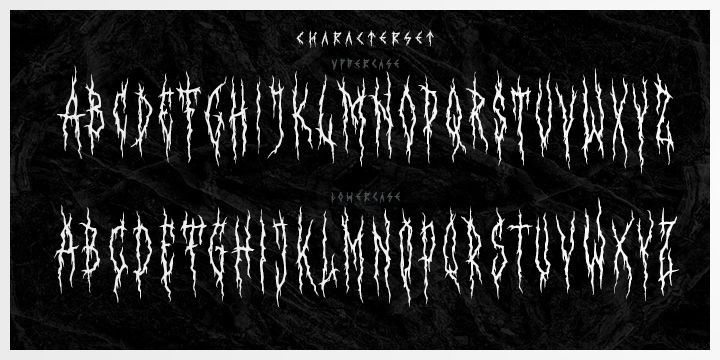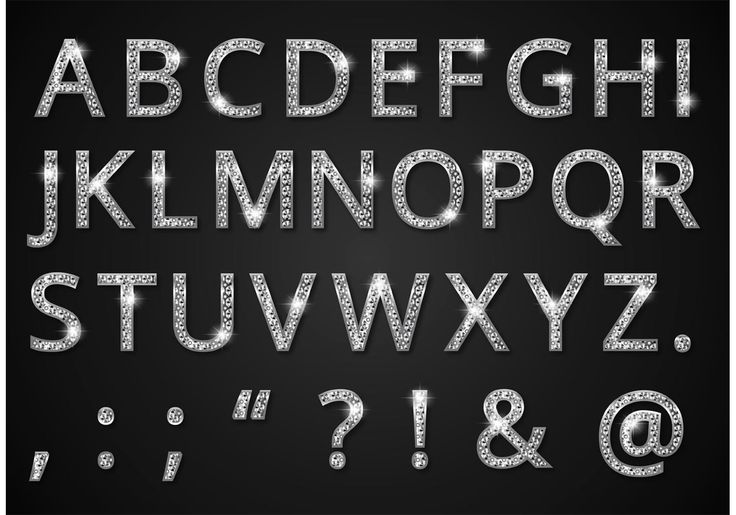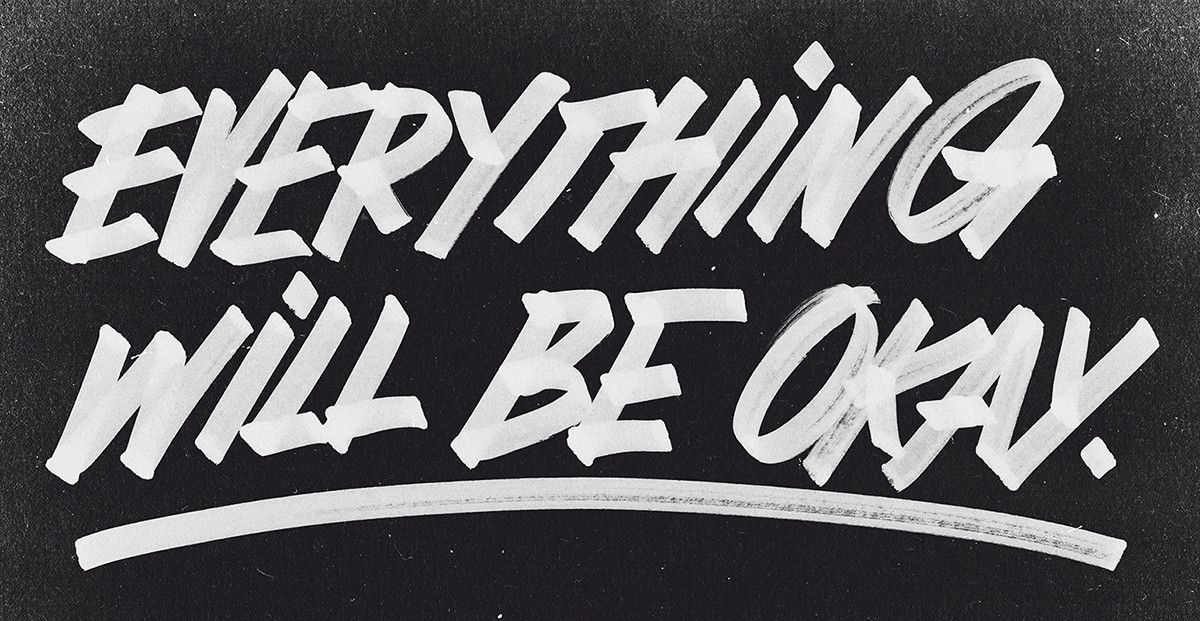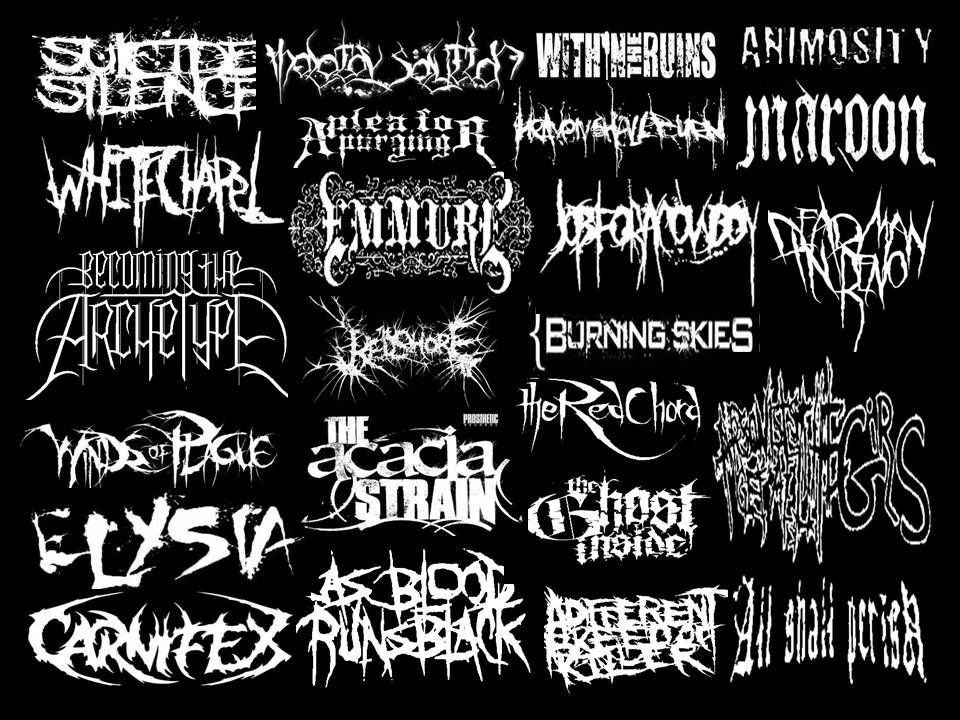
Шрифты для обложек треков: Дизайнерские шрифты | Шрифты Онлайн
Дизайн обложки альбома на основе типографики | by PFY (Твой фотошоп)
Обложки альбомов с типографикой уникальны тем, что они должны держать свои собственные — обычно минимальные (или дополнительные) художественные приемы, чтобы создать интерес или донести идею. Шрифт — это основное. По этой причине я бы предложила уделить дополнительное внимание, даже больше, чем обычно, выразительности шрифта.
Помните, я говорю о том, как текст общается визуально.
No Doubt “Rock Steady” — Gwen Stefani (Album Art Concept), Jolie Clemens (Album Design & Layout)
Например, посмотрите на обложку этого альбома для No Doubt “Rock Steady”. На ней только шрифт. Некоторые части выделены красным — заметьте, как это привлекает наше внимание, в то время как черный шрифт остается второстепенным.
Представьте себе эту концепцию с другим шрифтом — что-то действительно совсем другое, например, с Times New Roman.
Все выглядело бы совсем иначе, верно? Вероятно, мы бы потеряли эту энергичную атмосферу. Исходник имеет довольно органичные мазки кистью, но равномерные засечки заставили бы все выглядеть значительно более жестким. Основная мысль здесь не в том, что Times New Roman скучен, а в том, что сам шрифт, как визуальный элемент, обладает коммуникативными свойствами.
Давайте проиллюстрируем эту идею дальше на базовом примере.
Мы будем работать с обложкой тестового альбома — воображаемый альбом воображаемой группы под названием “The Album” от Example Band.
Приведенный выше пример довольно пресный. Это черный текст на белом фоне. Шрифт непритязательный. Выглядит незаконченным, не так ли? Это выглядит скучно, скучно … здесь действительно не на что обратить внимание, и фокус не выделен.
Обратите внимание, как внешний вид самой гарнитуры шрифта потенциально меняет способ его взаимодействия.
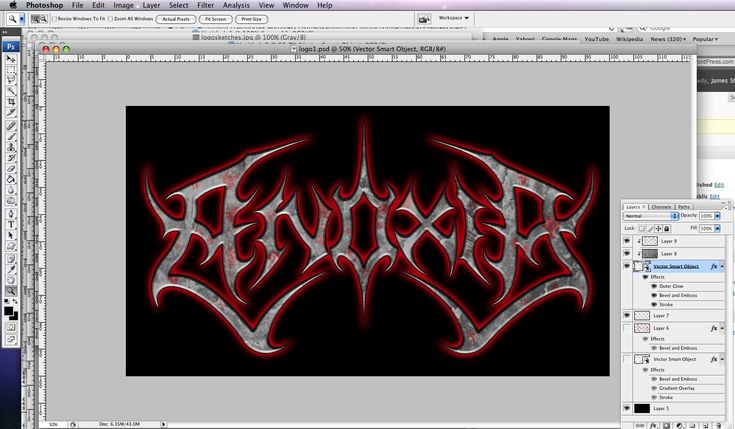
Эти три примера очень разные, хотя сами макеты довольно похожи.
Слева мы имеем жирный, богато украшенный шрифт (шрифт Braton Composer). Название альбома написано заглавными буквами, и оно очень большое. И действительно “кричит” зрителю. Обратите внимание, что масштаб (один из принципов дизайна) помогает подчеркнуть, что заголовок большой и громкий; название группы в сравнении намного меньше.
В центре шрифт выглядит рукописно (шрифт Brittany Signature Script). В этом есть человеческий фактор, который кажется довольно личным и органичным — буквы несовершенны. О какой музыке это заставляет вас думать?
Справа тип довольно геометрический и равномерный (шрифт Voyager). Как это визуально коммуницирует с вами по сравнению с двумя другими?
Мы можем развивать эту идею дальше, когда начнем включать в состав другие элементы искусства и принципы дизайна. Например, цвет очень коммуникативный, как и близость и визуальные соотношения, которые разделяют различные части вашей композиции.
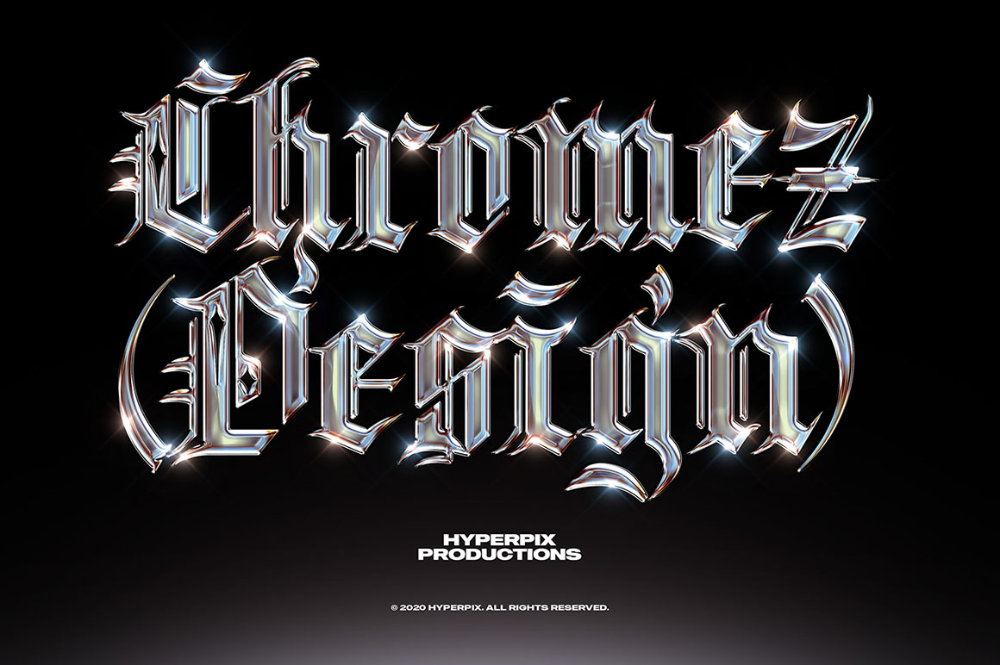
Давайте возьмем эту идею и рассмотрим еще несколько примеров.
Blood Sweat and Tears “Greatest Hits” Album Art
Вот обложка Blood, Sweat, and Tears’ Greatest Hits. На ней используется шрифт woodblock, чтобы прописать название группы. Все дополнено белым текстом шрифтом без засечек; обратите внимание, как этот шрифт дополняет больший. Почему? Есть несколько причин: он меньше, и менее декоративный.
Но как это визуально коммуницирует? Я бы сказала, что это намекает на возраст. Эти буквы были напечатаны раньше; они были тут и они видели какие-то события. Это визуально передает идею «крови, пота и слез» — фраза, часто связанная с тяжелым трудом и самоотдачей.
Duran Duran “Big Thing” Album Art
Вот интересная обложка — это альбом Duran Duran “Big Thing”. Обратите внимание, что буквы “I” там как бы и нет; она создается с помощью отрицательного пространства в композиции. Сами слова разделены и разъединены. Они также «втиснуты» в квадратные пространства.
Этот дизайн 1988 года, и он показывает — обратите внимание на выбор цвета, эстетику. Знание трендов и использование их могут пойти на пользу дизайну; что может поднять его визуальную привлекательность.
Что касается общения, обратите внимание, насколько «большие» (“big”) здесь буквы. Они, как правило, большие и громкие, с добавлением акцента на слово “big”. Также интересно отметить, что это было посвящением Энди Уорхолу, который умер годом ранее. Работа Уорхола часто отличалась схожим блочным направлением с насыщенными цветами — возможно, это была намеренная отсылка.
Beyoncé “Beyoncé” Album Art — Todd Tourso (Designer)
Бейонсе — мощная фигура в поп культуре, и это интересная обложка, не так ли? Дизайн довольно минималистичный, но это и не плохо. Лично я считаю минимализм потенциально очень успешным, но также сложным направлением для успешного воплощения.
В этом случае у нас есть жирный, строгий шрифт на черном. Имя, изолированное в этом пространстве, в приглушенном розовом цвете. У него сильный контраст с фоном, поэтому оно по-настоящему привлекает внимание. Я бы сказала, что оно говорит о том, что оно «больше, чем жизнь» или «не нуждается в представлении». Это уверенный дизайн.
41. Временный
. Черный вес напоминает деревянную надпись маршрутизатора.
42. Кейли
У Кейли отчетливое женственное чувство, которое принимает смелое отношение, чтобы соответствовать ее формам.
43. Директора Cut Pro
46. Engravers Gothic
47. Bombshell Pro
Bombshell Pro — это шрифт для ручной каллиграфии, который включает в себя длинные связи между буквами, что позволяет создавать красивые заголовки или подписи.
48. Брэндон Текст